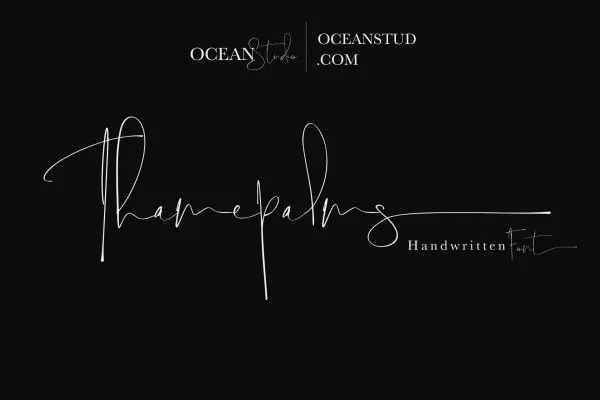
A fonte Thamepalms é uma criação cheia de personalidade e curvas, desenvolvida para imitar um estilo de escrita à mão livre com um toque natural. Ela foi criada através de traços rápidos que dão ao texto um aspecto orgânico em um mundo digital. Essencialmente inspirada no hábito de escrever de mãos naturais, as linhas elegantes revelam o verdadeiro significado dos caracteres e são complementadas com finalizações de letras longas para aprimorar seu tipo. Esta font oferece uma versão única para aqueles que buscam um estilo autêntico em suas criações digitais. Ideal para designers procurando por algo diferente, Thamepalms é perfeitamente adaptado à categoria de script fonts.